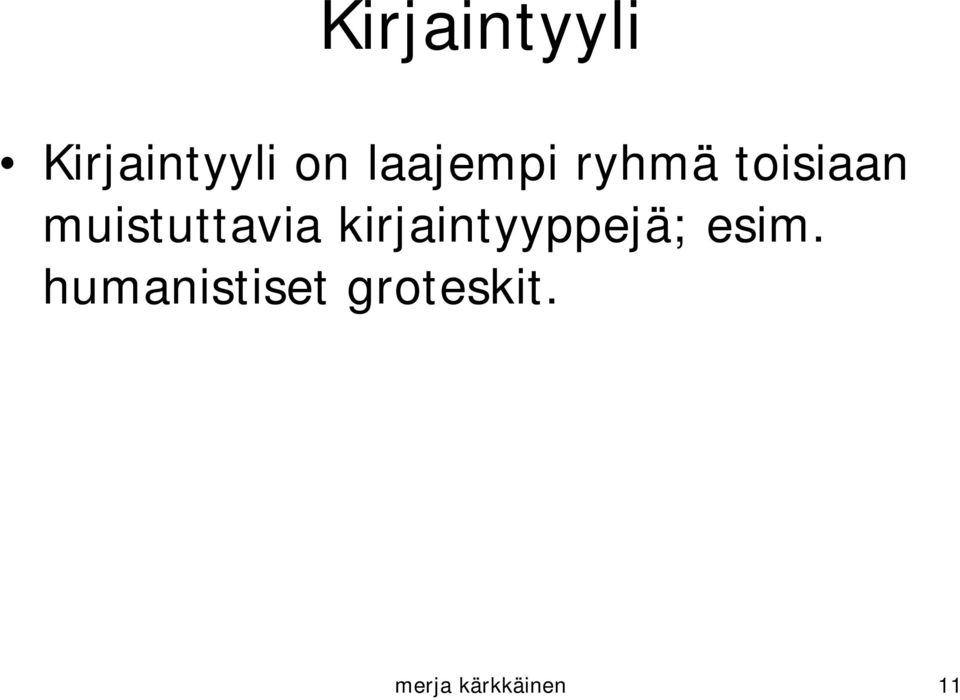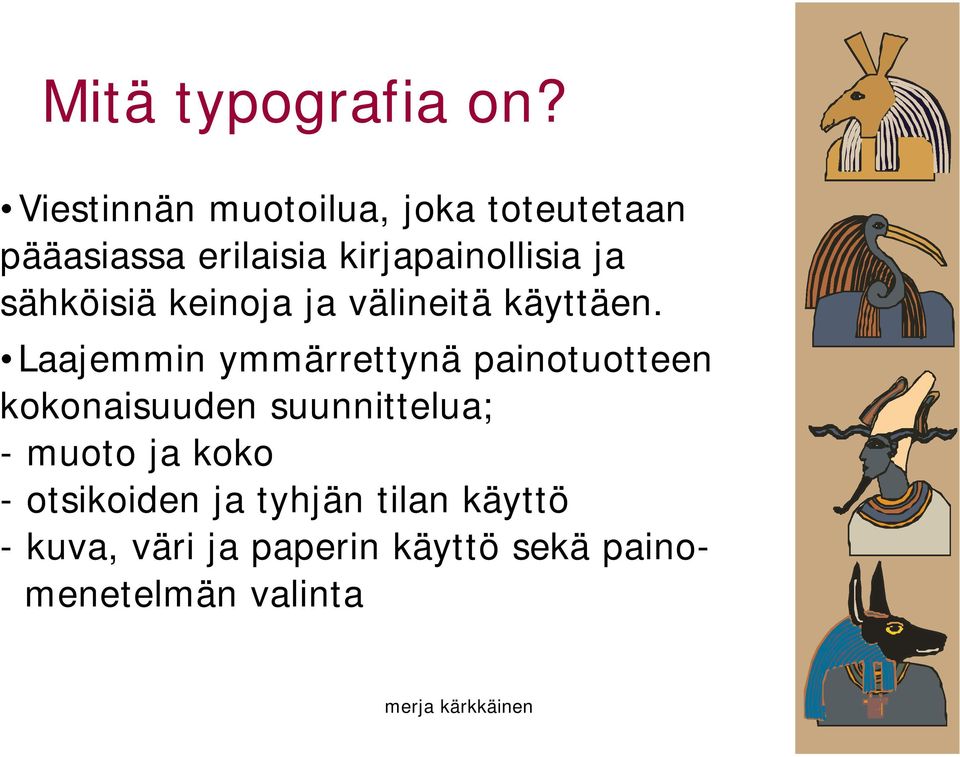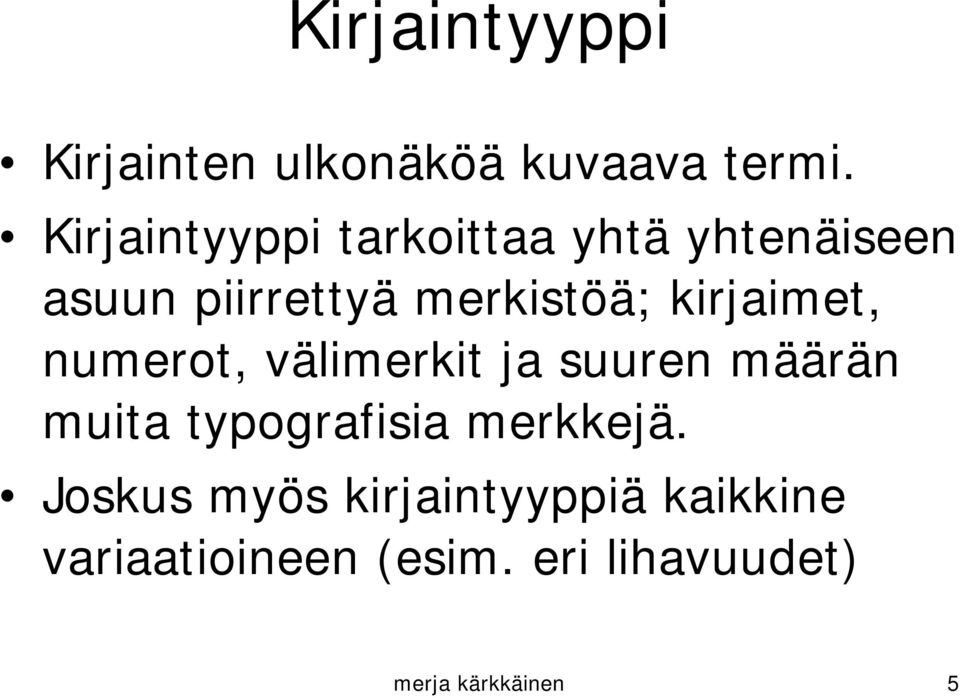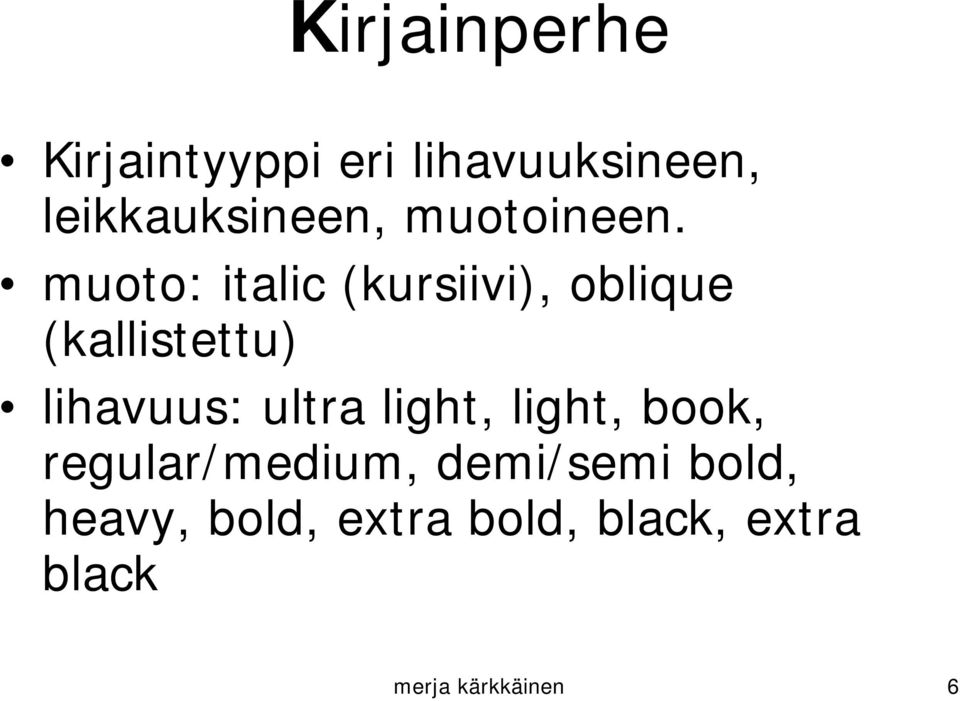
A a. A a. Kirjaintyylit ja -tyypit. TYPOGRAFIA turkuamk Visuaalinen viestintä. merja kärkkäinen 1
1 A a A a Kirjaintyylit ja -tyypit TYPOGRAFIA turkuamk Visuaalinen viestintä merja kärkkäinen 1
2 Mitä typografia on? Viestinnän muotoilua, joka toteutetaan pääasiassa erilaisia kirjapainollisia ja sähköisiä keinoja ja välineitä käyttäen. Laajemmin ymmärrettynä painotuotteen kokonaisuuden suunnittelua; - muoto ja koko - otsikoiden ja tyhjän tilan käyttö - kuva, väri ja paperin käyttö sekä painomenetelmän valinta merja kärkkäinen 2
3 Typografia verkossa Typografiaan kuuluu ulkoasun kokonaisuuden suunnittelu: - muoto ja koko - tekstin ja tyhjän tilan käyttö -kuva -väri - erilaiset audiovisuaaliset tehokeinot merja kärkkäinen 3
4 Kirjaintyyppi? Kirjasinleikkaus, fontti, kirjainperhe, kirjaintyyli. Erilaisia nimityksiä ja termejä sekavaa käyttöä. Mitä käsitteet sitten tarkoittavat? merja kärkkäinen 4
5 Kirjaintyyppi Kirjainten ulkonäköä kuvaava termi. Kirjaintyyppi tarkoittaa yhtä yhtenäiseen asuun piirrettyä merkistöä; kirjaimet, numerot, välimerkit ja suuren määrän muita typografisia merkkejä. Joskus myös kirjaintyyppiä kaikkine variaatioineen (esim. eri lihavuudet) merja kärkkäinen 5
6 Kirjainperhe Kirjaintyyppi eri lihavuuksineen, leikkauksineen, muotoineen. muoto: italic (kursiivi), oblique (kallistettu) lihavuus: ultra light, light, book, regular/medium, demi/semi bold, heavy, bold, extra bold, black, extra black merja kärkkäinen 6
7 Kirjainleikkaus Yksi ainoa merkistö, esim. lihavuudet ovat omia, itsenäisiä leikkauksia. Niitä ei saada aikaan ohjelman konekursivoinnilla tai boldauksella, vrt. insinöörikursiivi. merja kärkkäinen 7
8 Fontti Fontti tulee ranskan sanasta fondre (=valaa, valmistaa). Alussa se on tarkoittanut vain yhtä kokoa esim. 10-pisteiseksi valettua merkistöä. Jokainen koko oli oma fonttinsa. Nykyään arkikielessä sama kuin kirjaintyyppi. merja kärkkäinen 8
9 Mikä on kirjasin? Virheellisesti kutsutaan kirjaintyyppiä. Kirjasin oli metalliladonnan aikakautena kirjakkeessa oleva kohokuvio, joka painoa paperille kirjaimen tai merkin. Tietokoneessa niitä ei ole. Kirjainmuodot tallessa nyt digitaalisina tiedostoina. merja kärkkäinen 9
10 Milloin kirjasin-nimitys? Kun puhutaan tai 1600-luvun alkuperäisistä metallisista renessanssiantiikvasta, kirjasin-sana on paikallaan. Nämä olivat olemassa kirjakkeina ja kirjasimina. Pahimpia levittäjiä ovat tietokoneohjelmien suomennokset (alkuperäisessä on yleensä font). merja kärkkäinen 10
11 Kirjaintyyli on laajempi ryhmä toisiaan muistuttavia kirjaintyyppejä; esim. humanistiset groteskit. merja kärkkäinen 11
12 Jaottelua fontti kirjaintyyppi kirjainleikkaus esim. Linotype Syntax Regular kirjainperhe esim. kaikki Linotype Syntaxit kirjaintyyli esim. humanistiset groteskit merja kärkkäinen 12
13 Kirjainten eri osat merja kärkkäinen 13
14 Kirjainten X-korkeus merja kärkkäinen 14
15 merja kärkkäinen 15
16 Kirjaintyyppien luokittelua (Olof Erikssonin mukaan) 1.Goottilaistyyliset (murretut kirjainmuodot) Tekstuura Rotunda Swabach Fraktuura Tiivis ja kapea tekstuura on näistä vanhin, peräisin 1300-luvulta, vallalla Pohjois-Euroopassa. Johann Gutenbergin käyttämät varhaiset painokirjaimet. merja kärkkäinen 16
17 2. Antiikvat a.vanhemmat antiikvat (renessanssiantiikvat, garaldit) Adolf Rusch, Strasbourg, 1467 Aldus Pius Manutius, 1495 ensimmäinen kursiivi, 1501 Venetsia Bembo (1929), 1499 Garamond, 1531 Nordisk antikva, 1907 Berling, ITC Galliard, Goudy, Granjon, Palatino, Minion jne. Renesanssiantiikvat ovat luettavia, kauniita ja kehitetty pitkien tekstien, kirjojen lukemista varten. merja kärkkäinen 17
18 b. Siirtymäkauden antiikvat (barokkiantiikvat) 1600-luvun hollantilaisantiikvat: Elzevir, Janson, Kis ja Plantin Caslon, 1720 Baskerville, 1752 Times, 1932 Stanley Morrison, alkuaan sanomalehtikäyttöön Fournier, 1740, keveämpi mitä Baskerville ja Caslon Rokokoosta muistuttava Fleischmann, 1739 Siirtymäkauden antiikvoista Baskerville suosituin. Hyvä luettavuus, huolimatta lisääntyvästä kontrastista Muita; Bell, Bulmer, Caledonia ja Perpetua. merja kärkkäinen 18
19 e. Uusantiikvat (liittyvät uusklassismiin) Didot, 1700-luvun loppu (ranskalaista eleganssia) Bodoni, 1780, tunnetuin (satoja variaatioita Giambattista Bodonilta) Century Roman 1896, Century Oldstyle 1909 ja Century Schoolbook 1919 Bodoni & Futura kiinnostava kontrasti! Ohuiden ja paksujen viivojen jyrkkä kontrasti johtui kirjoitusvälineiden kehityksestä. Bodoni ja Didot ovat kirjaintyyppejä. Voi edustaa mutta myös epäonnistua. merja kärkkäinen 19
20 d. Päätteettömät antiikvat Optima, 1958 Pascal, 1968 lisää Colonia, Stellar jne. Poikkeus säännöistä, päätteetön päätteellinen kirjaintyyppi! merja kärkkäinen 20